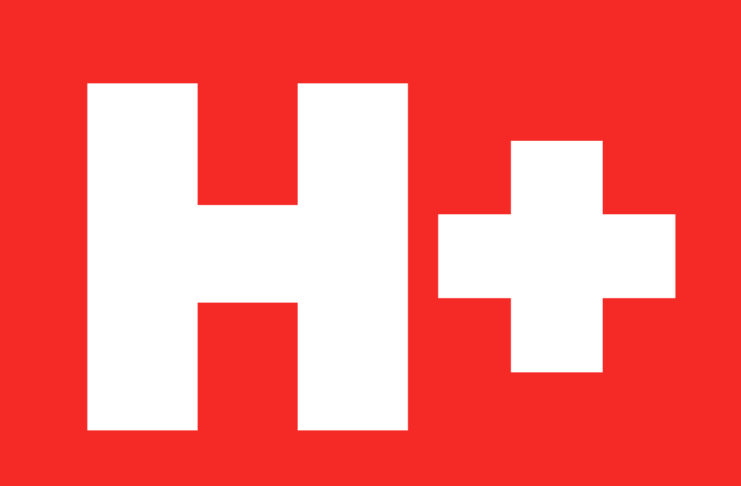
Il rilascio della nuova versione dell’Helvetica (chiamato Helvetica Now) è estremamente importante, molto più di quanto sembri e che porta inesorabilmente con se conseguenze che saranno chiare, perlomeno agli addetti ai lavori, solo tra diversi anni.
Il nuovo design del font è pensato per essere attuale, pur mantenendo quel profilo di classico che da sempre l’ha contraddistinto sin dalla nascita, ma soprattutto per essere al passo con le nuove tecnologie, soprattutto per quanto riguarda i display ad alta risoluzione: una sfida molto difficile perché negli ultimi anni le scelte di mercato hanno imposto standard proprietari anche nei font e emergere nel mercato di adesso è di certo più difficile di un tempo.
Ma per capire la portata di questa rivoluzione dobbiamo guardare la faccenda da un punto di vista molto diverso e ampio: cambiare il font più usato al mondo non è semplice, comporta responsabilità enormi legate all’emozione, alla leggibilità, alla fattibilità di un business e della comunicazione nella sua più intima realizzazione.
Ma d’altra parte questa è una delle tante sfide che l’Helvetica ha dovuto affrontare nella sua storia, nata come la Cenerentola delle font e diventata sin da subito la regina della comunicazione a 360°.
Helvetica, quasi per caso
Si perché nel 1957, quando Max Miedinger, ex dipendente diventato (probabilmente a forza) freelance Svizzero, è incaricato dalla fonderia Haas di Münchenstein (piccola città di confine) di sviluppare un carattere senza grazie in grado di risollevare le nefaste sorti economiche, non immaginava i risvolti che ne sarebbero emersi.
Miedinger elaborò una nuova edizione del Akzidenz Grotesk, uno dei caratteri senza grazie più utilizzati all’epoca il cui disegno originale risale al 1896 (dalla fonderia H. Berthold AG), dandole il nome di Neue Haas Grotesk.
Il nome fu cambiato poi in Helvetica (da Helvetia, definizione latina della Svizzera) quando fu acquistato e distribuito dalle società Stempel e Linotype pochi anni più tardi probabilmente per una più facile penetrazione nel mercato internazionale.
Ma nonostante il successo del font Akzidenz Grotesk non subì nell’immediato forti scossoni, la svolta per il nuovo font di Miedinger arrivò quasi subito: Hans Neuburg lo recensisce nel numero 4 del 1959 della famosa rivista “Neue Grafik” parlandone come del nuovo Akzidenz Grotesk e citando letteralmente che l’Helvetica è il font “(…) a cui non abbiamo alcuna intenzione di rinunciare”.
Due anni dopo la distribuzione tramite Linotype (soprattutto) ne stabilisce un successo che cresce in modo esponenziale per tutta la decade successiva e arriva sino ai giorni nostri: la cultura degli anni sessanta (meno negli anni settanta dove l’estremismo porta a scelta qua e la diverse) è fortemente influenzata dall’Helvetica in tutti i suoi stili.
Con l’arrivo del digitale la conferma dell’Helvetica è forte: Apple lo include tra i caratteri presenti all’interno del primo Macintosh e QuarkXPress lo definisce come font di default nello stile Normale, sostanzialmente imponendolo come scelta primaria in tutti i tipi di impaginazioni grafiche del mondo, con grandissimo successo anche in Italia.
Nel 1989 Massimo Vignelli lo sceglie come font ufficiale per la segnaletica della città di New York, riscoprendolo in modo più razionale e da li in avanti il carattere è identificato come una impronta tipica dello stile Italo-svizzero moderno all’estero: nel mondo del business sono in molti ad apprezzarne l’armonia, la modernità e la formalità tanto che Microsoft lo sceglie per il proprio logo e Apple per tutti i testi dell’interfaccia nei propri device dal 2007 al 2015: l’Helvetica padroneggia i device a risoluzione normale, l’Helvetica Neue (primo ridesign del 1983) per i device retina, a risoluzione maggiore. Nel 2015 l’avvicendamento con il nuovo font San Francisco.
Luci e ombre
Difficile, e a tratti presuntuoso, definire in poche righe il perché di un successo così ampio dell’Helvetica nel mercato, rispetto a molte altre font con, sulla carta, tutte le armi per vincere. L’Univers di Adrian Frutiger, ad esempio, riporta la stessa età dell’Helvetica con anche le stesse radici grafiche tratte dal Akzidenz Grotesk, ma in questo caso con una elaborazione più moderna e originale, specie in alcuni glifi come la “G” e la “Q” e proprio per questo suo aspetto reso una scelta volontaria da parte dei grafici, laddove l’Helvetica appare più trasparente e meno deciso.
Forse gli anni sessanta hanno dimostrato da una parte la voglia di ritorno a linee più classiche nel design, pur senza un radicale sconvolgimento della geometria di font come il Futura, che aveva spopolato nel mezzo secolo prima e che tanto aveva dato alla comunicazione tra le due guerre.
D’altra parte l’autorità dell’Helvetica è cresciuta in modo così esponenziale negli anni sessanta, sfruttando una composizione sempre più capace che spesso si è accostato il termine “Design” all’utilizzo originale del font, più che al suo intrinseco disegno, nel pensiero di chi scrive forse una delle più evidenti chiavi del successo.
Questo può mantenere tutti i benefici offerti negli anni dall’Helvetica, con però una impronta nuova, sottile e indefinita ai più, che ravviva un design consolidato senza stravolgerlo e dando allo stesso tempo quella trasparente ed efficace personalità che con il tempo si è forse persa nell’abuso di più o meno tutti.